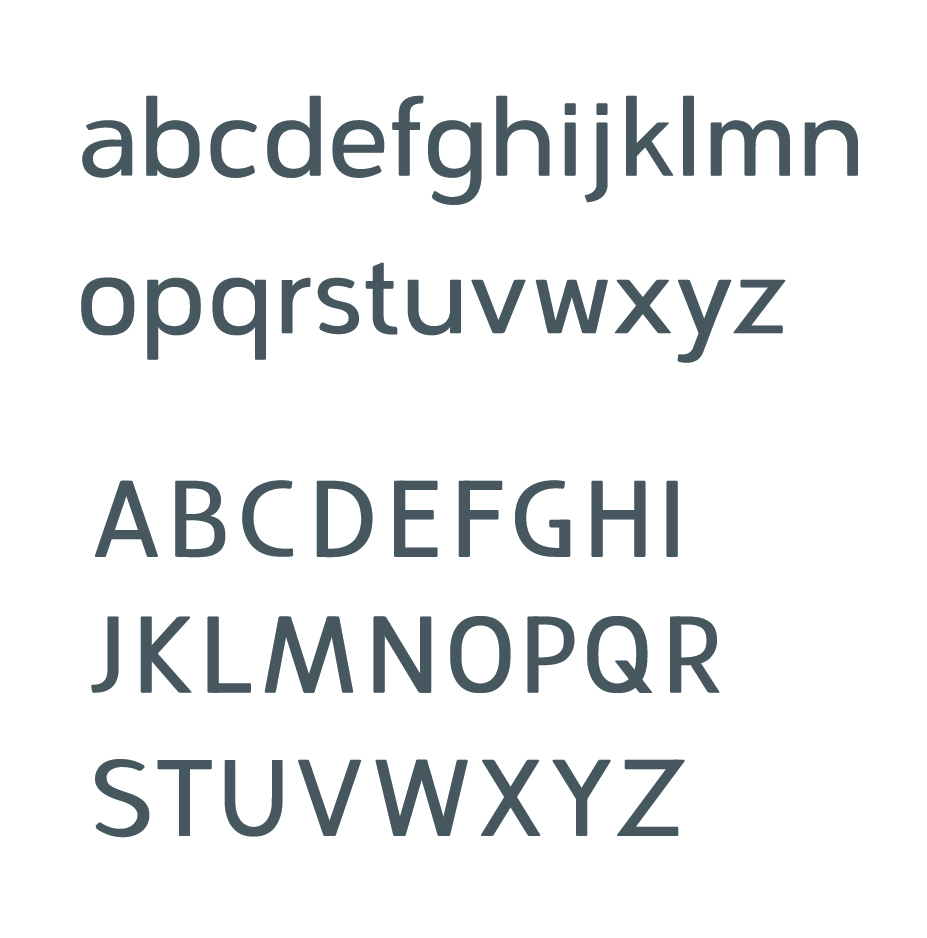
Signaletica stellt sich der Kritik
da ich das hohe Niveau dieses Forums bzw. der Beiträge und der Feedbacks sehr zu schätzen weiß, habe ich mich dazu entschieden, die Buchstaben meiner Signaletica hier vorzustellen.
Ich freue mich natürlich über jede hilfreiche Anregung von Euch.
Hintergrundinformation:
Mit der Signaletica möchte ich – wie der Name schon verrät – eine Schrift für den Einsatz im Orientierungsdesign entwickeln.
ich mach sowas ja sehr ungern aber hier stimmt wirklich einiges nicht.
das s kippelt nach links.
d, c, b, p, q, g, h, u, n, v, x sind zu breit und passen harmonisch nicht zum rest
auch die strichstärke bei einigen buchstaben varriert zu stark (vergleich mal v, w, x mit s und a)
das gleiche betrifft auch die versalien (M, Q vs. S, C)
das S rutscht nach links
Z ist zu spitz und zu steil
vorschlag: schau die mal univers und frutiger an und versuche die zeichen harmonische anzugleichen.
momentan sieht es wie ein mix zwischen condensed (G) und extended (g, u) schnitt aus.
Orientierungsdesign
hmm, ohne dir nahe treten zu wollen, traust du dir das wirklich zu?
ich habe einiges an verständniss für schrift und würde mir das niemals zutrauen, zumal es
schon sehr gute schriften in diesem bereich gibt. warum also das rad neu erfinden? als übung
vielleicht ganz nett aber wenn du eine professionelle schrift entwerfen willst, wirst du dich noch
einige monate damit beschäftigen müssen bist alles passt.
ohne unfreundlich sein zu wollen: ich sehe hier auch mehr probleme als lösungen. an deiner stelle würde ich diesen versuch erst mal beiseite legen und mich intensiv mit einzelnen zeichen gelungener schriften beschäftigen, also: anschauen, vermessen, abpausen, nachzeichnen usw. dass in deiner schriftart zum beispiel mit dem ›s‹ etwas nicht stimmt, siehst du vermutlich selbst – aber um das ausbessern zu können, musst du erst mal wissen, wie ein ›s‹ aussieht, das eine harmonisch wirkende strichstärke hat und nicht nach links kippt. man kann sicher darüber streiten, aber ich persönlich fand imitation in vielen fällen einen geeigneten ansatz, um handwerkliche grundlagen zu erlernen. dass man an dem imitierten dann punkte entdeckt, die man gerne anders machen würde, ist der erste schritt in richtung eigenständigkeit. bevor man damit anfängt, schadet es meines erachtens aber nicht, ein paar hundert frutiger-›a‹ oder helvetica-›s‹ gezeichnet zu haben.
Es ist noch kein Meister vom Himmel gefallen.
Ich hoffe, die Kritik motiviert Dich, weiter zu arbeiten!
Ich sehe das als einen ersten Entwurf, eine grobe Skizze, an. Es passt kein Buchstabe wirklich zum anderen, die Details haben die Vorredner ja schon aufgezählt. Das G scheint einer anderen Schrift entsprungen zu sein, das passt von der Form nicht.
Ja,
es handelt sich um einen ersten Ansatz und eure Kritik spornt mich an. Natürlich bin ich nicht davon ausgegangen, dass ich hier die Schrift hochlade und nur Lorbeeren ernte. Es ging mir ja genau darum, dass ich von anderen erfahrenen Gestaltern gesagt bekomme, was nicht passt.
Das kippende "s" ist mir – richtig vermutet – auch schon aufgefallen.
Sicher kann es noch monate dauern, bis es passt. Dann dauert es halt so lange.
Ich möchte deshalb eine Schrift für Orientierungsdesign entwickeln, weil es zwar schon einige gibt die auf eine gute Lesbarkeit getrimmt wurden doch der Aspekt der Barrierefreiheit vernachlässigt wurde. Da die aber – besonders für öffentlich zugänliche Gebäude nicht nur ein immer aktuelleres Thema ist sondern bereits gesetzliche Vorschrift, will ich genau hier ansätzen. Sicherlich kann es sein, dass der Aspekt der Barrierefreiheit und die Ästhetik kollidieren können (Beispiel"G"). Es geht hierbei darum, einen Weg zu finden, der beides vereint.
Das sollen keine Ausreden sein sondern die Idde hinter der Schrift erklären. Ich hoffe, selbst wenn es mich Monate kostet, das Ihr mich dennoch auf diesem Weg weiter begleitet.
Die breit-stehenden buchstaben sollen der guten Lesbarkeit auf Entfernung dienen. Vielleicht stehen einige Buchstaben aber wirklich ein wenig zu weit.
Ich werde micht jetzt mal an die Überarbeitung der bisher genannten Punkte machen.
wie wirkt sich denn der Aspekt der Barrierefreiheit auf einen Font aus? Meinst Du damit besondere Pictogramme oder eine Eigenschaft der Schriftgestaltung, z. B. für Sehbehinderte optimiert?
PS: wie ich eben sah, trieb Pachulke die selbe Frage um ... :-)
Barrierefreiheit im Orientierungsdesign bezieht sich auf die Taktilität bzw. gute Tastbarkeit einer Schrift.
Hierzu werden die Buchstaben nur in Versalien genutzt. Einige mikrotypografische Aspekte in Bezug auf die Anatomie der Buchstaben müssen hierfür berücksichtigt werden.
Am Anfang reicht es, wenn man sich in einen Blinden hineinversetzt um grundlegende Punkte zu ermitteln. Darüber hinaus muss man sich mit aktueller Forschung zu diesem Thema auseinander setzten und am Ende ist der Beste Weg das Treffen mit Blinden in Blindenvereinen um dort Details mit den Betroffenen zu dikutieren.
sind bdpq einfach das gleiche zeichen gedreht? so drängt es mir zumindest auf (disclaimer: ich habe von typographie und dergleichen so gut wie überhaupt keine ahnung). wenn ja, ist es nicht kontraproduktiv für eine informierende schrift (stichwort barrierefreiheit).
Sorry, ich dachte an die Versalien – und hätte es auch so explizit schreiben sollen!
Bist Du sicher, daß so ein spezielles Problem wie das, das Du Dir vorgenommen hast, ideal ist als Einstieg in die komplexe Welt der Schriftgestaltung? Sollte man da nicht zunächst mit etwas weniger schwierigem anfangen?
Nein, ich lass mich nicht entmutigen.